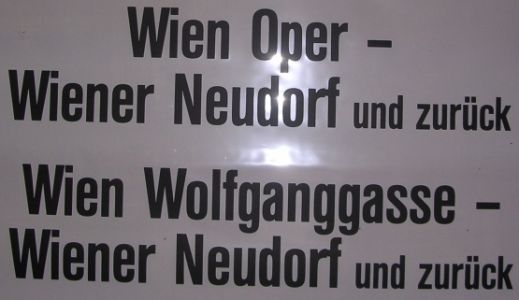
Kompakte Schrift ohne Schnörksel
Ich stehe irgendwie total auf der Leitung - diese Schrift kommt mir total bekannt vor, ich komme aber nicht drauf.
Helvetica Compact ist es nicht (das "a" endet hier gerade), aus der Zurich-Familie auch nicht.
Denke, das Rätsel ist ein sehr leichtes - wer kann helfen? Danke!
Probier ma die ganzen condensed/compressed Varianten der statischen
Grotesk-Schriften ala Helvetica, Univers, Folio, Imago, BlockGothic etc.
Da gibts ne Menge.
Oder – immerhin ähnlich – Sign Gothic und Reforma Grotesk.
Aber die Schildermacher modifizier(t)en oft auch persönlich vorhandene Schriften.
Mir ist schon eingefallen, woher die Schrift mir so bekannt vorkommt - die österreichische Kartenfirma schlechtin, die Firma Freytag + Berndt aus Wien, verwendet diese Schrift für alle ihre Karten (fett + schmal):
Besonders auffällig das "g" mit nur geringer Unterlänge, das "R" mit geraden Strich vertikal nach unten und ein "J" ohne Strich oben, dafür links einem vertikalen Strich nach oben.
Jetzt, wo es mehr Schriftbeispiele und Hinweise gibt - kann mir jemand helfen?
Ich denke, ich bin fündig geworden:
Linotype Univers® 510 Compressed Medium